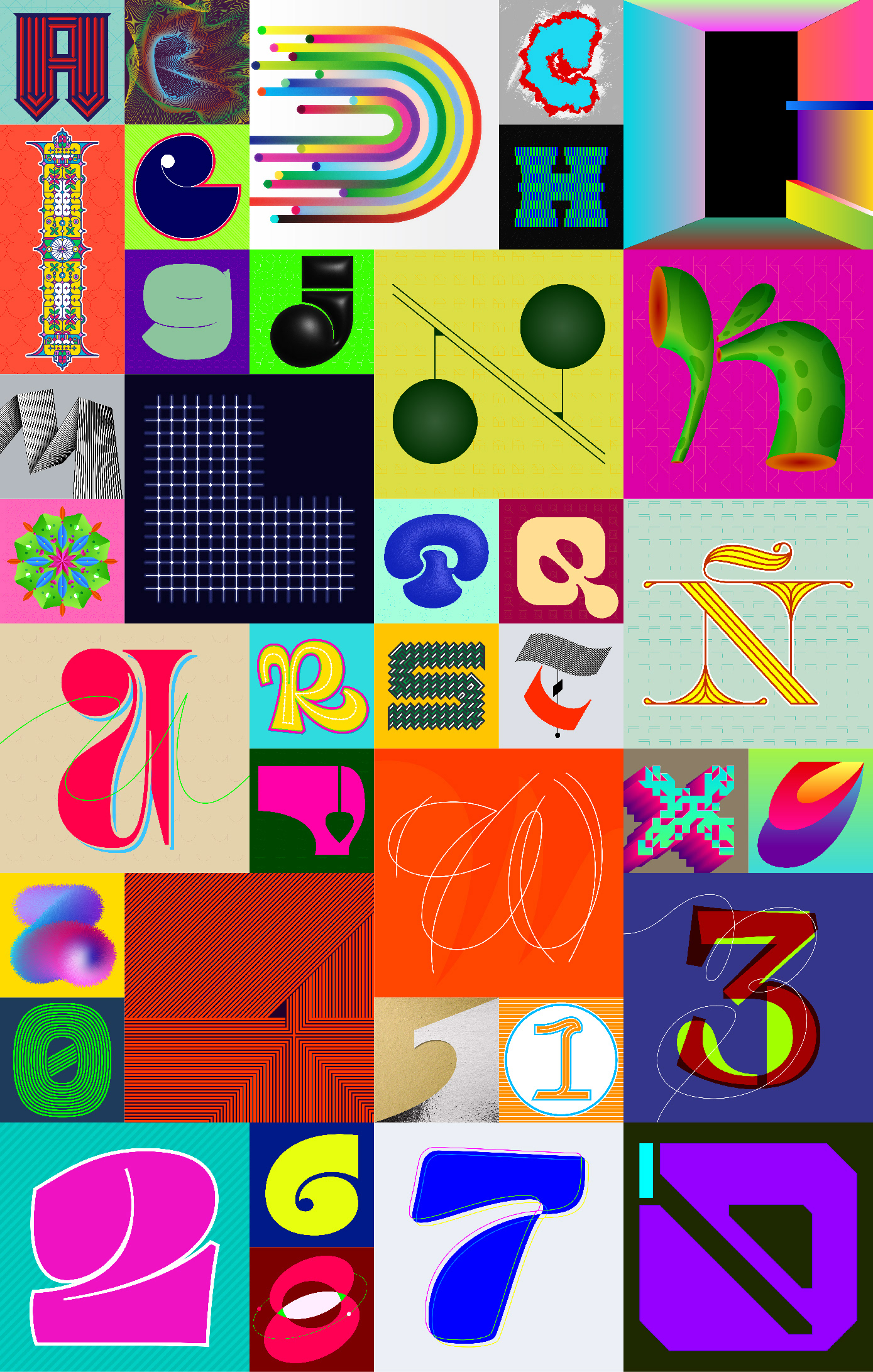
36 DAYS OF TYPE 2023
Serie de letras desarrolladas para el reto 36 days of type en su edición de 2023, con un perfil mucho más estético y display que permitió explorar de manera libre los límites y posibilidades del mapa de caracteres básico del sistema ISO latín, haciendo cada letra tanto más diferente de otra, pero conformando una gran colección de letras que muestran mi estilo de diseño.